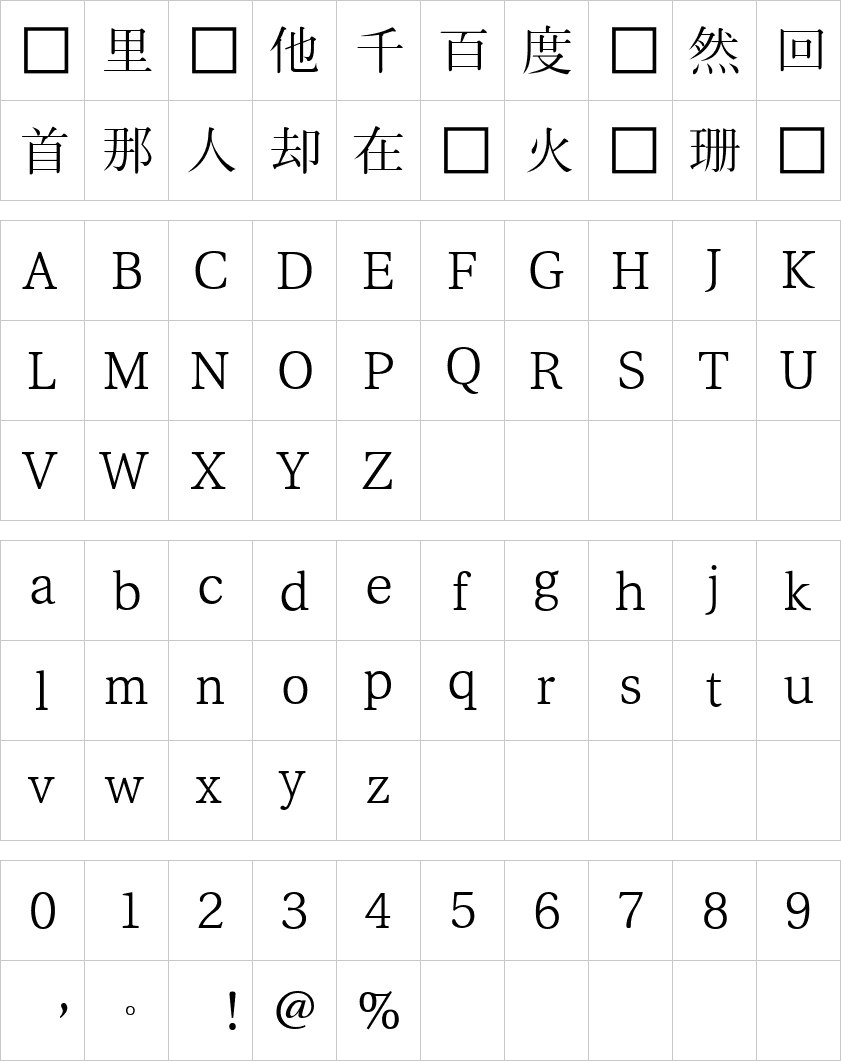
은 바탕
UnBatang是韩国Un开源系列字体中的其中一款,因为是韩国字体,为了方便中国大陆的小伙伴容易记忆,猫啃君给其起了个中文名“巴糖”,实际上并没有对字体文件做任何修改,这款字体在PS中的名字依然是“은 바탕”。
韩国Un系列字体是由@Koaunghi Un于1998年以HLaTeX type1制作而成,作者在20世纪90年代末制作type1字体用于韩国的Tex(JLaTex[1]),并以GNU GPL授权许可进行发布。于2003年,由@Won-kyu Park使用FontForge(PfaEdit)转换成ttf文件进行发布。
韩国Un系列字体包括核心系列9款字体和额外系列10款字体,猫啃网将会在稍后的时间逐一进行更新。不过较为可惜的是,这系列字体都是以繁体为主,支持简体的字数较少,中国大陆的小伙伴若要使用这套字体会比较难受。